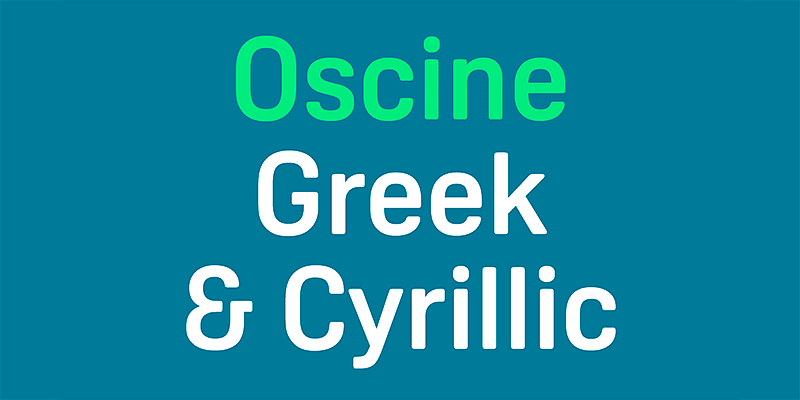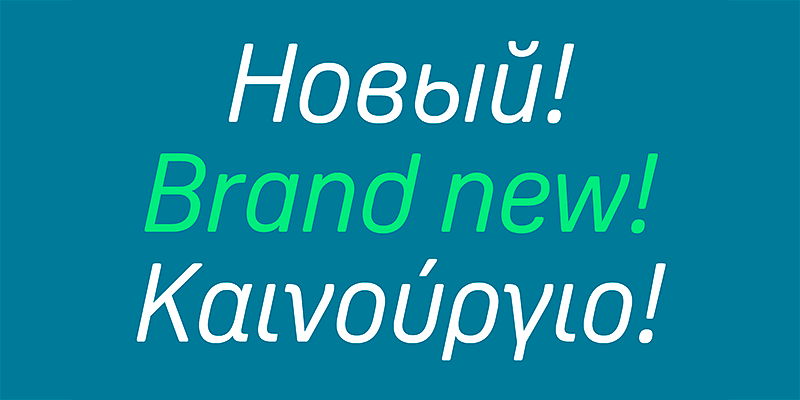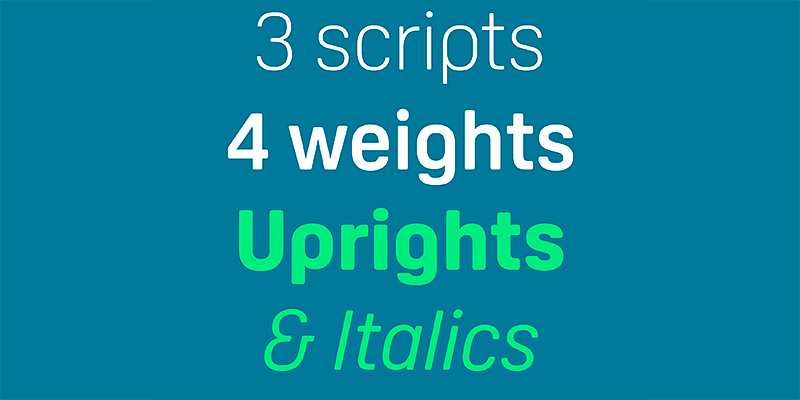
Oscine wirkt schmal und hat einen geometrischen Ausdruck. Sie kombiniert konventionelle Großbuchstaben mit einem ungewöhnlichen Kleinbuchstaben für Funktionalität mit genau der richtigen Menge an Charakter.